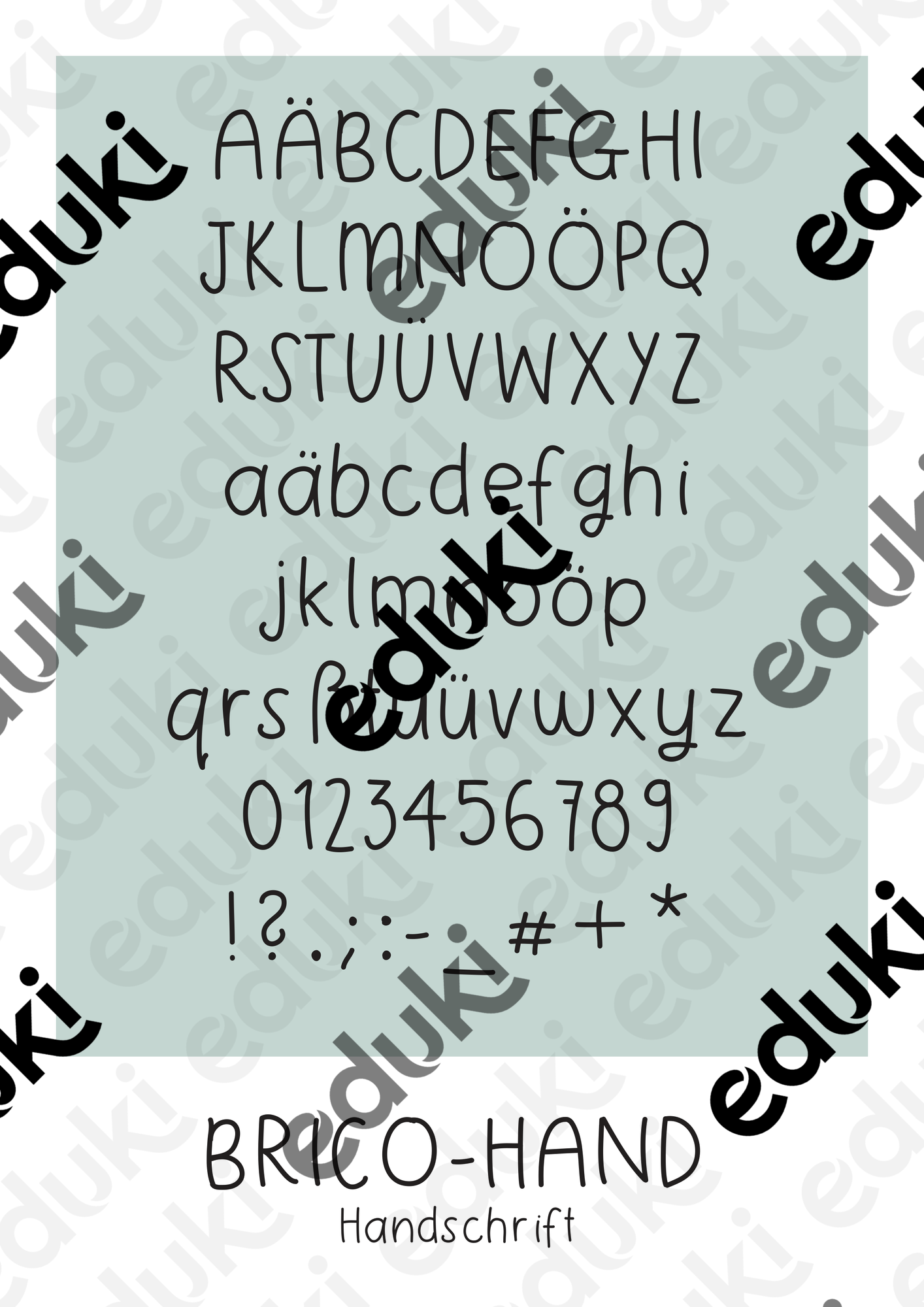
selbst erstellte Schriftarten - Schriftart für dein Arbeitsmaterial - Brico-Hand - Bricoliene - Deckblatt
Selbsterstellte, verspielte Handschrift, die sich wunderbar zur Erstellung von Arbeitsblättern oder anderem Unterrichtsmaterial eignet.
Schriftart für dein Arbeitsmaterial - Brico-Hand